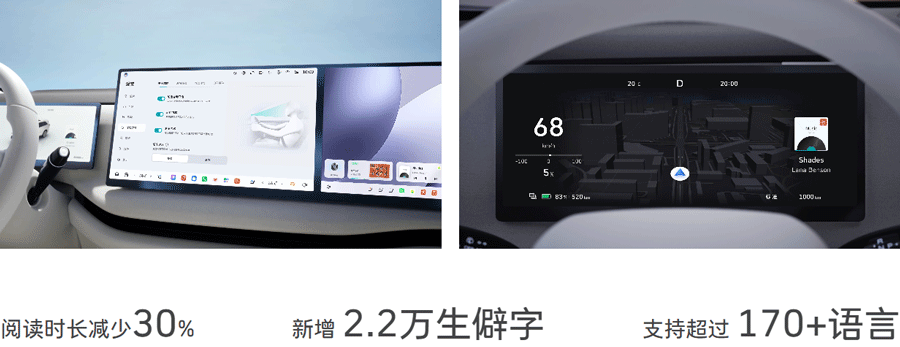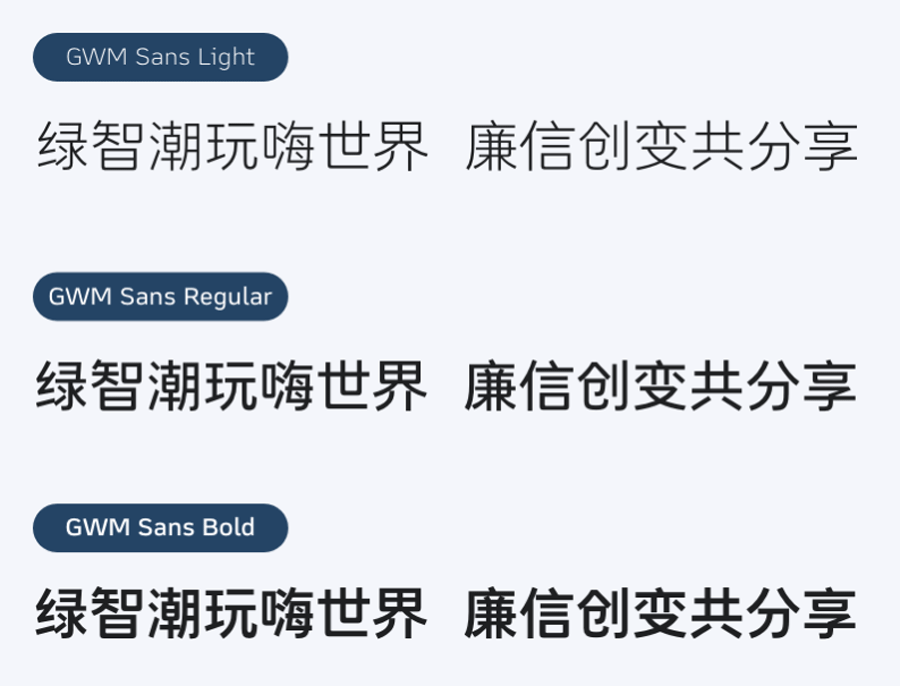
长城共享体(GWM Sans)是由长城汽车联合国际知名字体公司蒙纳字库(Monotype)历时 2 年精心打造的全球首款专为车载系统设计的中文字体,于 2026 年 1 月 30 日由原名”长城黑体”正式更名为”长城共享体”,并面向全球免费开放商用版权。
笔画设计圆润而不失力量,间距与行间距经过人机工学测试优化,增强视觉稳定性的同时也确保了瞬时识别效率。在车机局限性的环境下可以降低识别负荷、保障驾驶安全,目前已在国内外多款长城车型上搭载应用。当然,长城共享体也同样适用于其他各类需要清晰易读文字的场景,如智能设备、数字界面等。